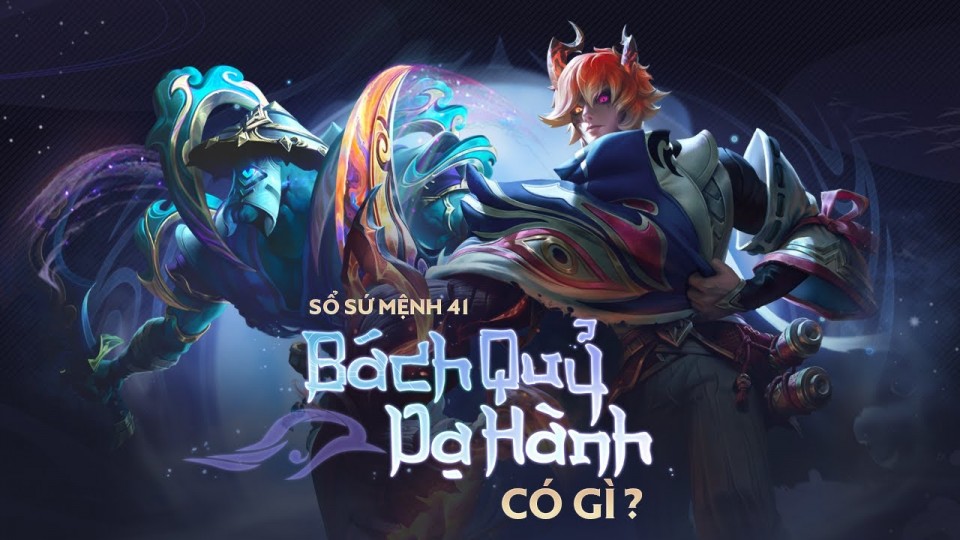
Giới thiệu về Font việt hòa LNTH aAnnyeongHaseyo
Trong thế giới thiết kế đồ họa hiện đại, việc tìm kiếm một bộ Font Chữ mang đậm phong cách văn hóa đặc trưng luôn là ưu tiên hàng đầu của các bạn học sinh và sinh viên. Font việt hòa LNTH aAnnyeongHaseyo là một trong những lựa chọn tuyệt vời nhất khi bạn muốn thổi hồn xứ sở Kim Chi vào các bài thuyết trình hay dự án sáng tạo của mình. Với các nét vẽ tròn trịa, mô phỏng cấu trúc chữ Hangeul, bộ font này tạo nên cảm giác thân thiện, trẻ trung và vô cùng dễ thương.
Đặc điểm nổi bật của phông chữ
Điểm mạnh nhất của bộ font này chính là sự tương thích hoàn hảo với bảng mã tiếng Việt. Người dùng không còn phải lo lắng về lỗi hiển thị dấu câu hay các ký tự đặc biệt. Font chữ sở hữu độ dày vừa phải, giúp văn bản dễ đọc trên cả nền tảng kỹ thuật số lẫn bản in. Đây là công cụ hỗ trợ đắc lực cho việc làm thiệp, thiết kế poster câu lạc bộ tiếng Hàn hoặc trang trí sổ tay cá nhân.
Cách ứng dụng Font việt hòa LNTH aAnnyeongHaseyo hiệu quả
Để tận dụng tối đa vẻ đẹp của bộ font này, bạn nên kết hợp với những gam màu pastel nhẹ nhàng như hồng nhạt, xanh lơ hoặc vàng kem. Đối với các bài tập nhóm, việc sử dụng font ở các tiêu đề chính sẽ giúp nội dung trở nên nổi bật và thu hút thị giác hơn. Đừng ngần ngại sử dụng font cho các video ngắn trên mạng xã hội để tạo sự đồng bộ với phong cách thẩm mỹ Hàn Quốc đang thịnh hành hiện nay.
Lưu ý khi sử dụng trong học tập
Mặc dù bộ font rất đẹp mắt, nhưng bạn hãy chú ý chỉ nên dùng cho các tiêu đề hoặc đoạn văn ngắn. Tránh sử dụng cho toàn bộ văn bản dài để đảm bảo tính chuyên nghiệp. Việc cài đặt font cũng rất đơn giản, chỉ cần tải về và cài vào hệ thống là có thể sử dụng ngay trên Word hoặc Canva.
Kết luận về bộ Font việt hòa LNTH aAnnyeongHaseyo